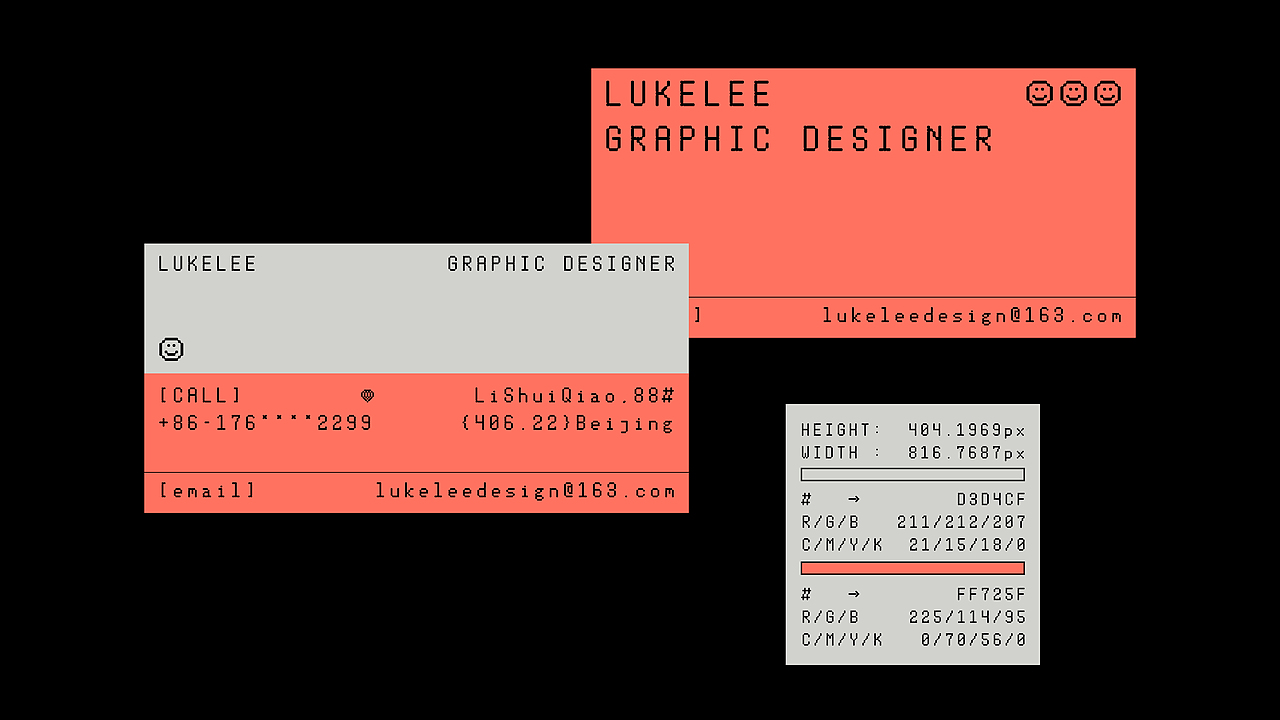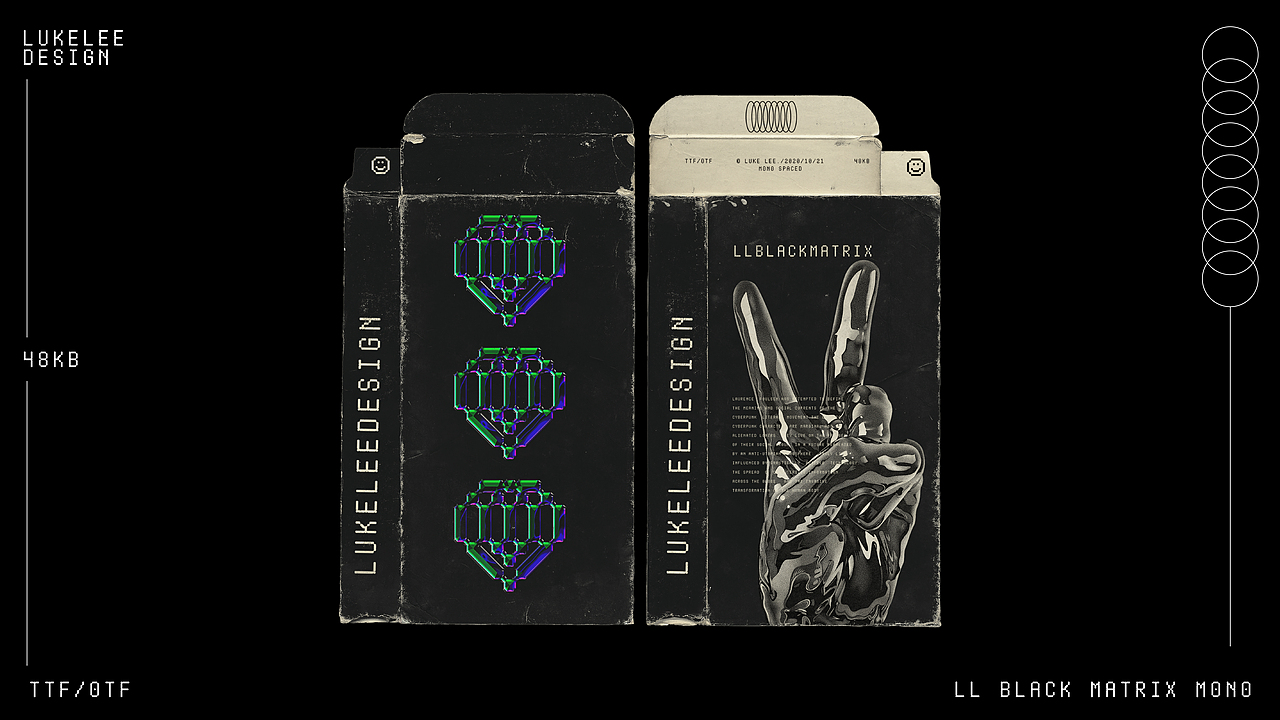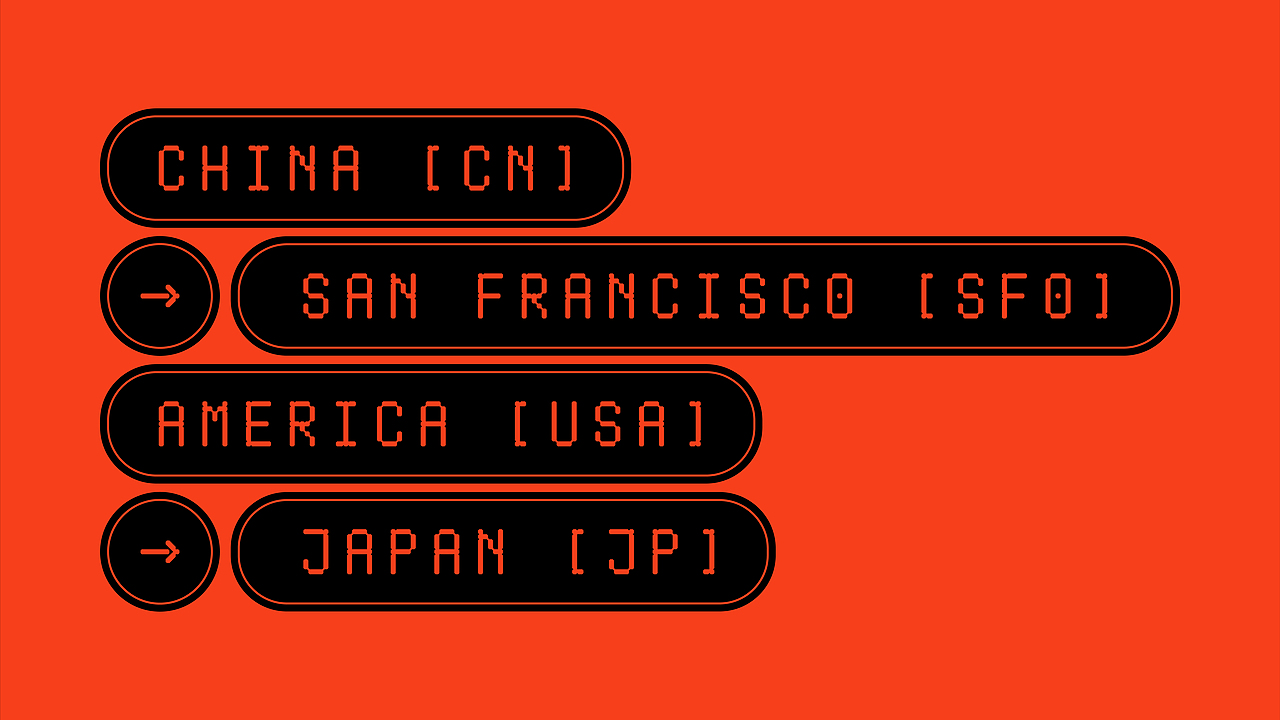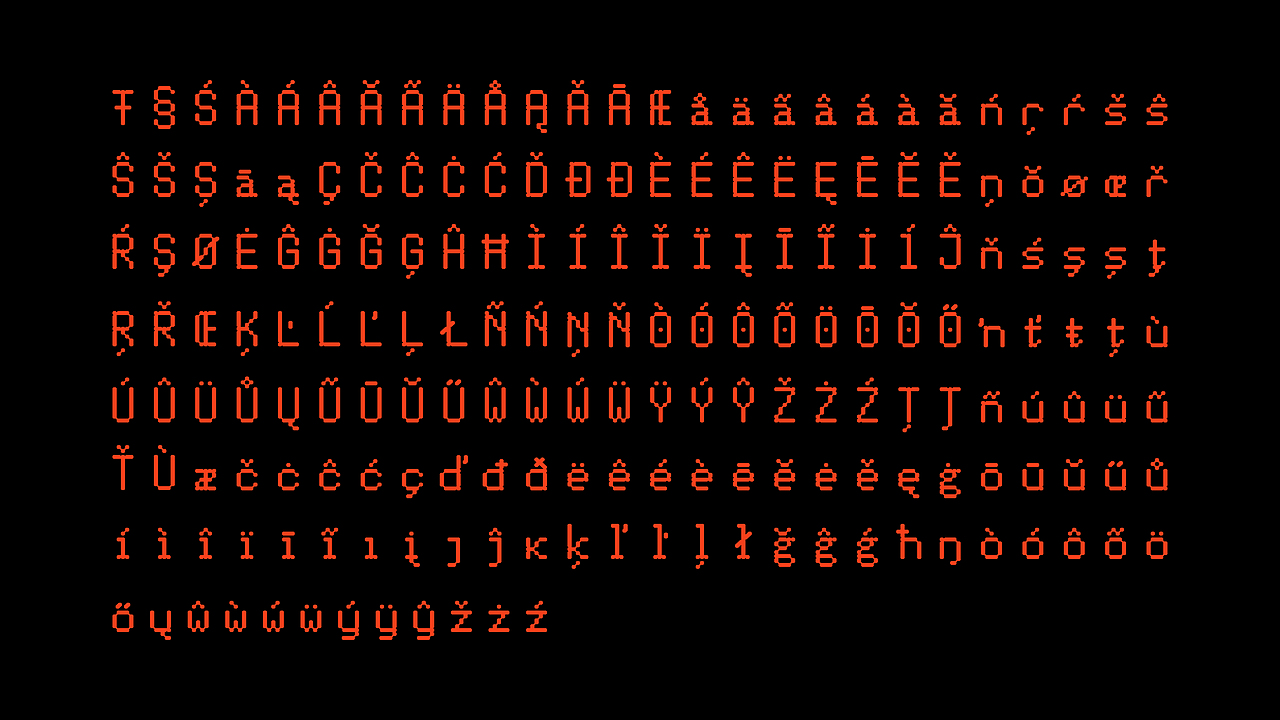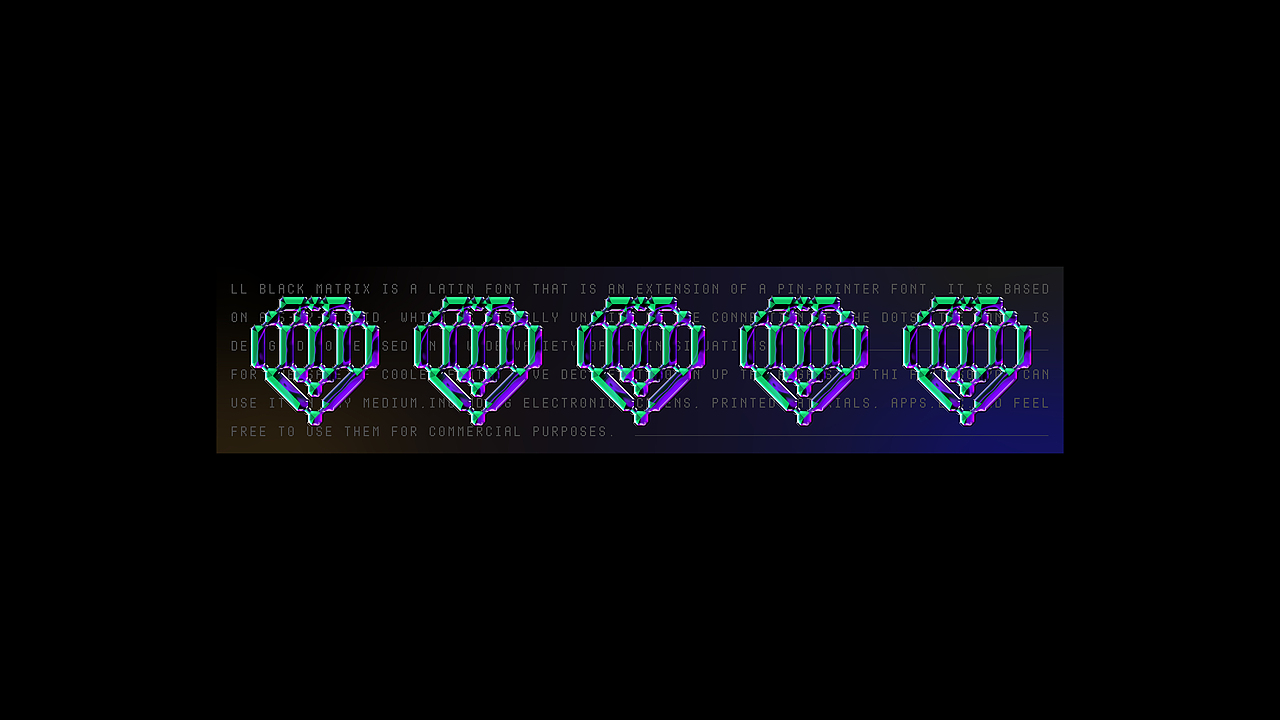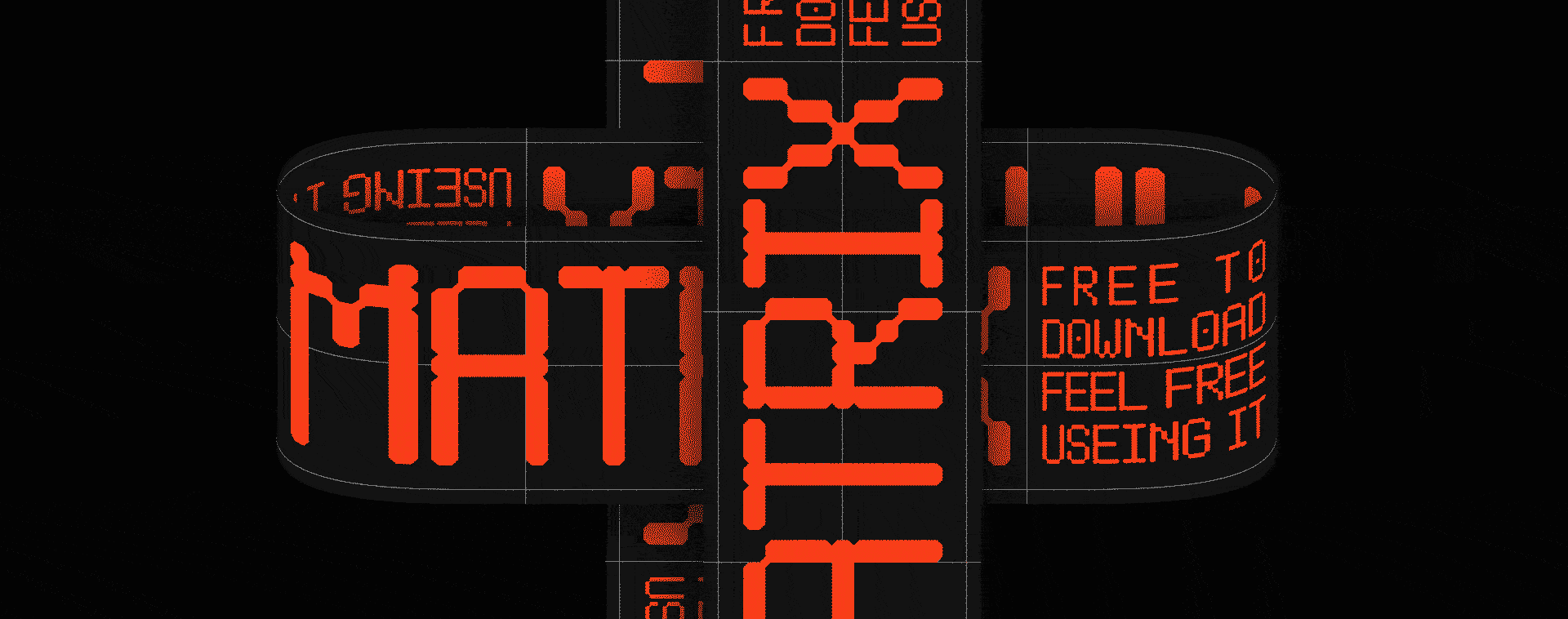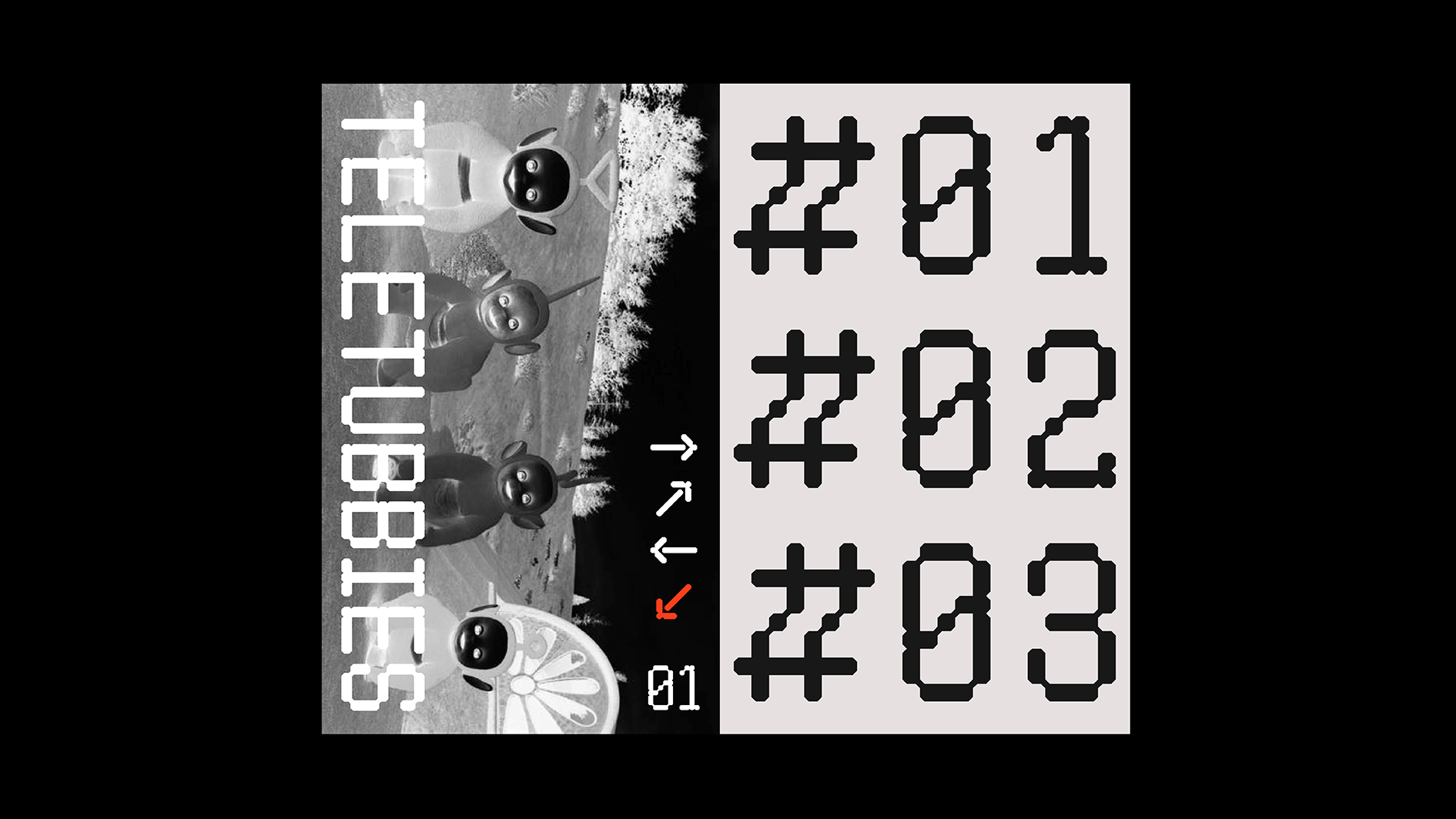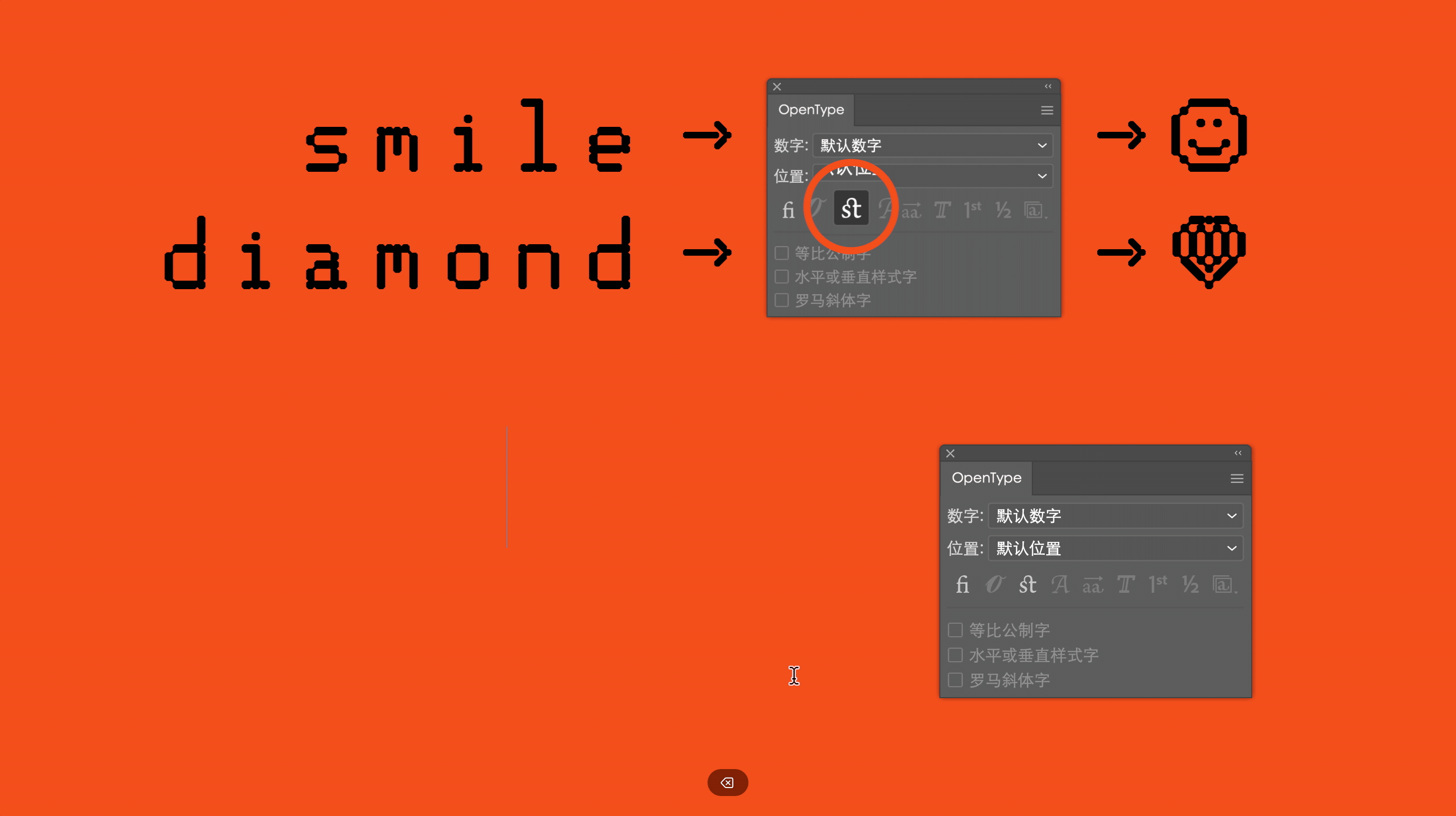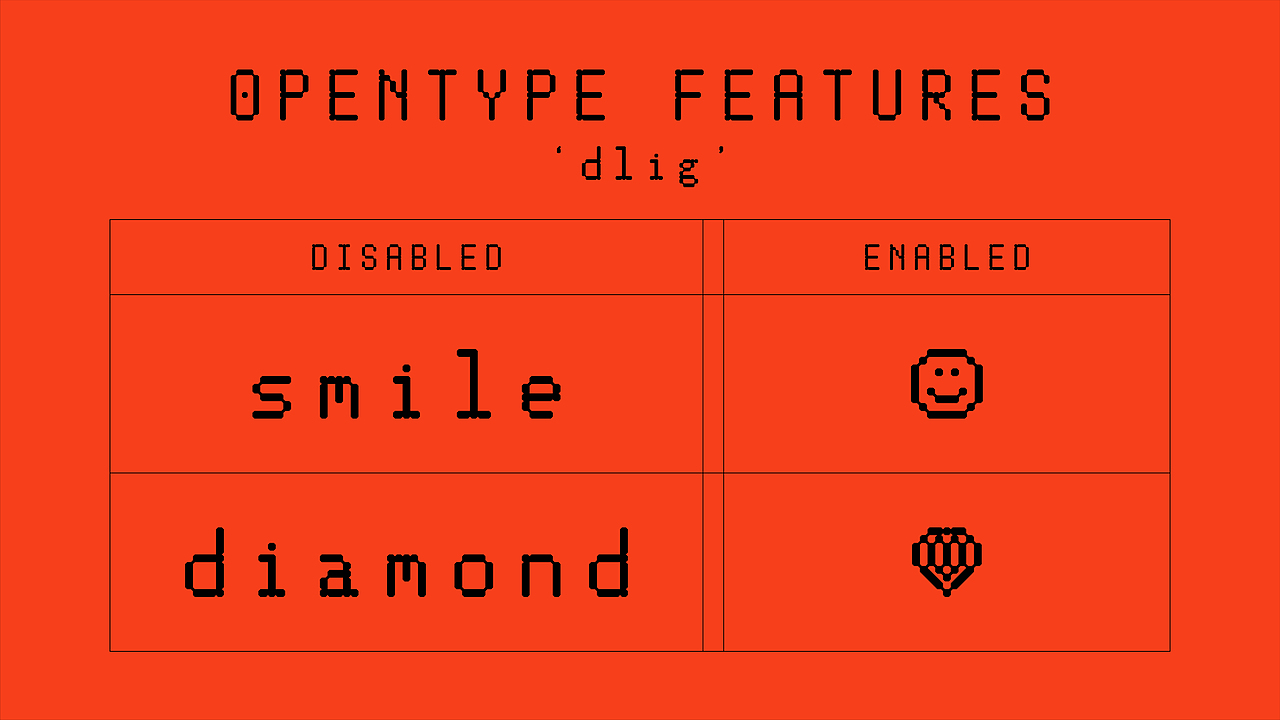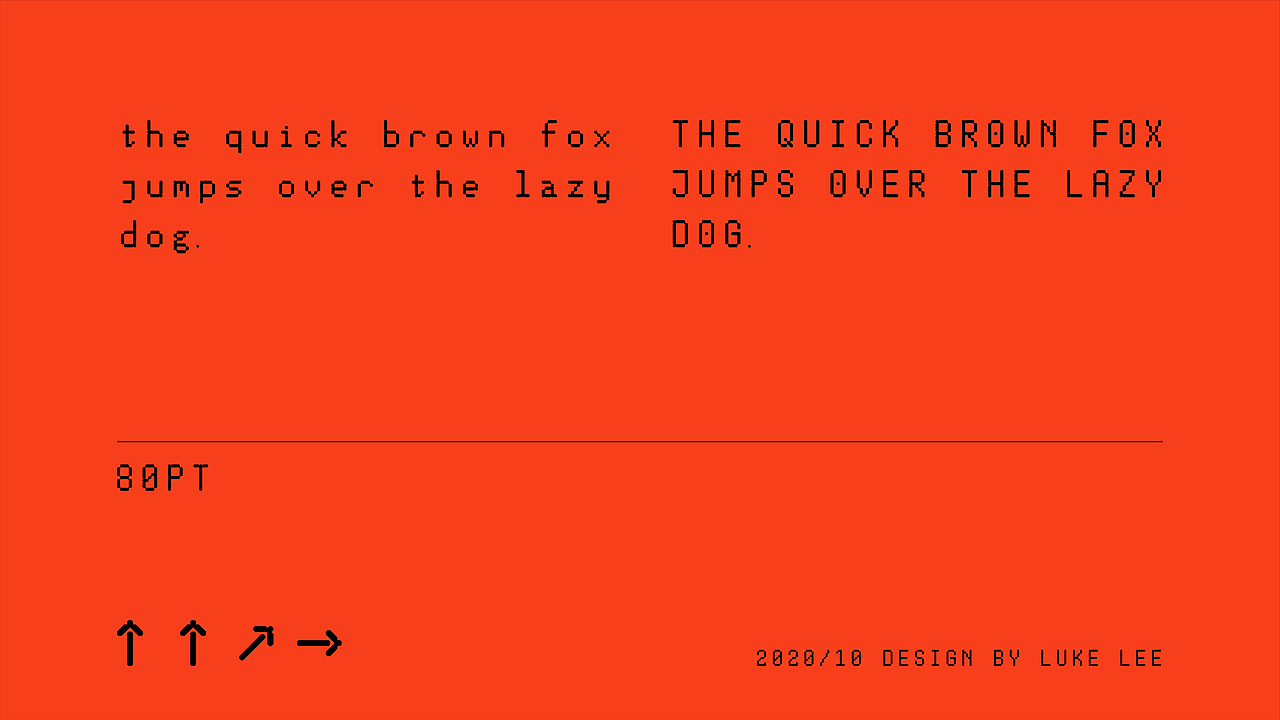
LL BLACK MATRIX|西文字体
LL Black Matrix是一款由针式打印机字体延伸而来的等宽拉丁文字体。这款字体基于5乘9的网格规范,并通过点阵连接使其在视觉效果上更统一。它包含300+字符并支持100+语言,可满足多种拉丁文使用场景。为了让大家无忧使用多样化字体,我决定开放这款字体的版权。
2.0版本在字距上做了等宽的处理,并且加入了Opentype feature,给生活来一点小惊喜。